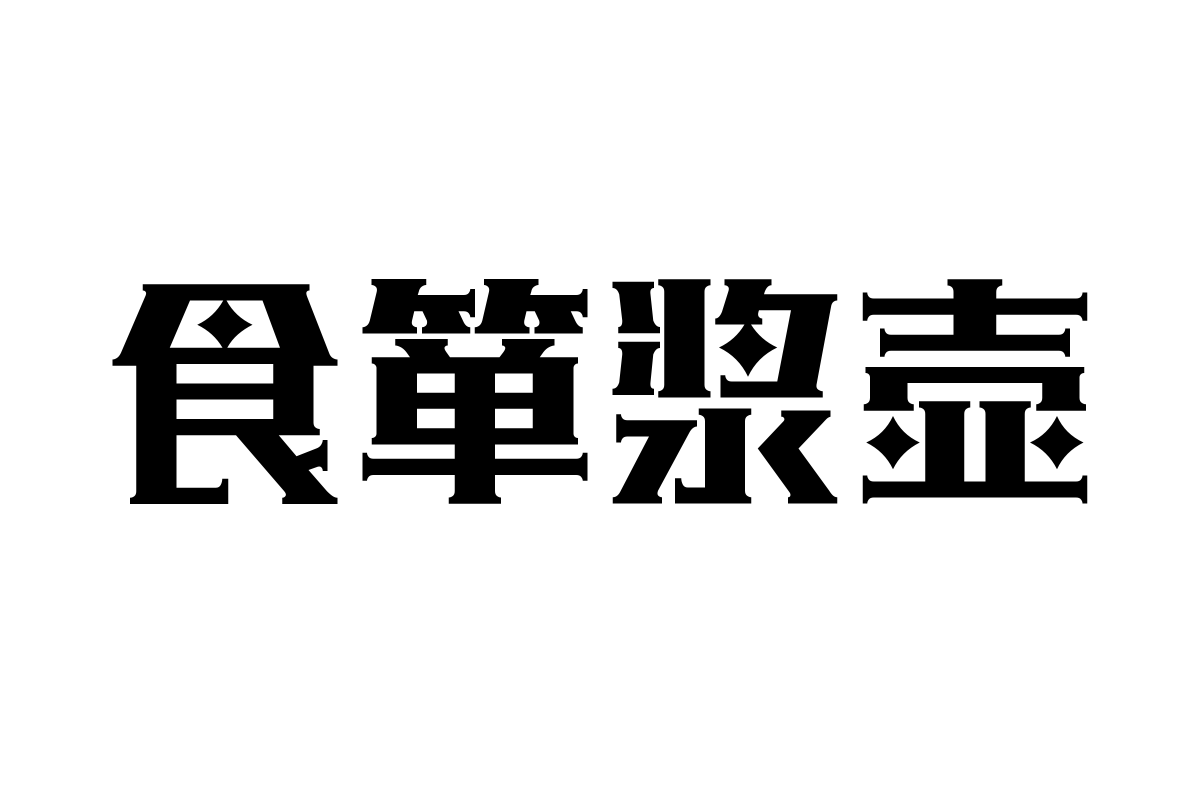
汉仪铸字黑是一款非常受欢迎的中文字体,其特点是笔画粗细分明,结构紧凑,给人一种强烈的视觉冲击力。这款字体广泛应用于各种印刷品和电子屏幕上,包括书籍、杂志、报纸、广告、网页等。
汉仪铸字黑的特点如下:
1. 笔画粗细分明:这款字体的笔画粗细变化明显,使得文字更加清晰易读。
2. 结构紧凑:汉仪铸字黑的结构紧凑,使得文字在有限的空间内展现出更多的信息。
3. 强烈的视觉冲击力:由于笔画粗细分明,使得文字在视觉上具有很强的冲击力,能够吸引人们的注意力。
4. 适用于多种场景:汉仪铸字黑适用于各种印刷品和电子屏幕,无论是在传统的印刷方式还是现代的数字媒体中,都能够很好地展现其特点。
总的来说,汉仪铸字黑是一款非常适合用于设计、出版、广告等领域的中文字体。